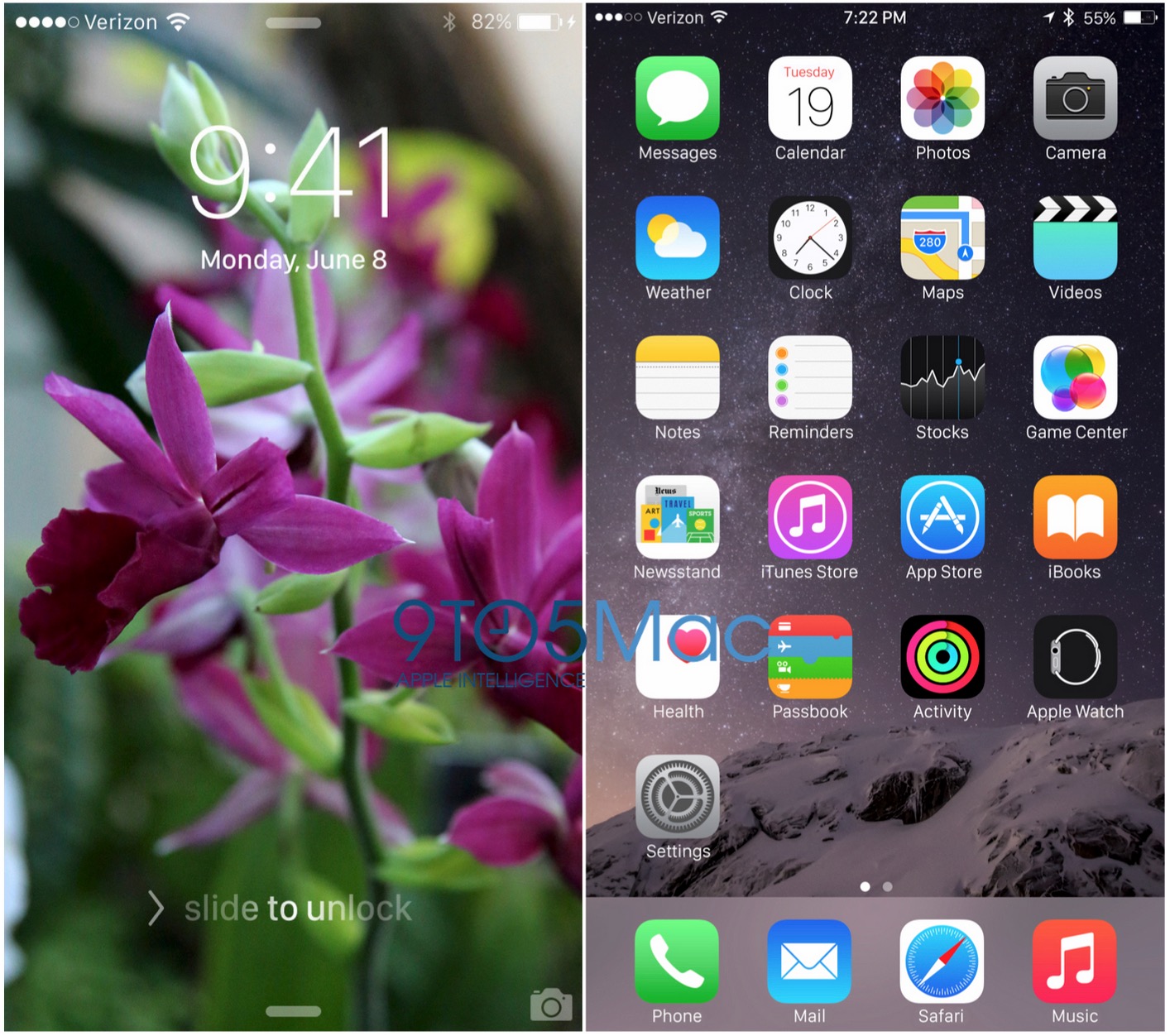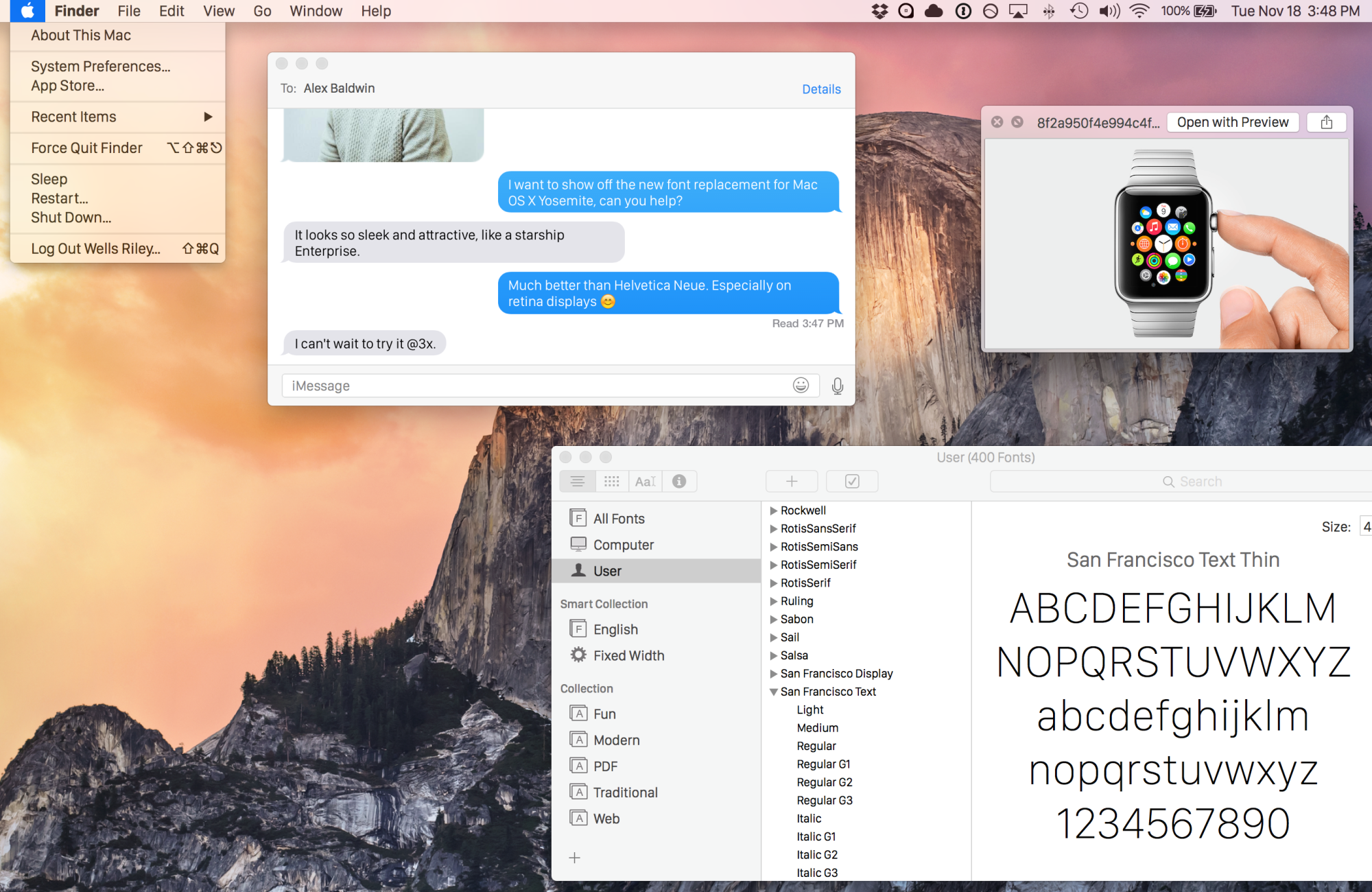
มีรายงานว่า Apple มีแผนที่จะใช้ตัวอักษรใหม่กับ iOS 9 ซึ่งจะมีแทนที่แบบเดิม ณ ตอนนี้ของ iOS 7, 8 ซึ่งใช้ Helvetica Neue อยู่ โดยพบว่าตัวอักษรใหม่นั้นมีชื่อว่า San Francisco ที่ใช้งานใน Apple Watch อยู่ ณ ตอนนี้
หน้าตาของแบบอักษรใหม่ตามข่าวที่แจ้ง (แบบปัจจุบัน iOS 7, 8 อยู่บนสุด)
ตัวฟอนท์ San Francisco นี้เห็นว่าอ่านง่าย, ปรับสเกลง่ายกว่าของเดิมจึงเป็นผลดีต่อนักพัฒนามากขึ้น
นอกจากฟอนท์นี้จะลงใน iOS 9 แล้วก็มีข่าวต่อว่าจะลงที่ OS X 10.11 ด้วยนะ ดังนั้นก็เลยมีคนแฮ็กเอาตัวฟอนท์ที่ว่านี้แทนที่ของเดิมซะเลย ภาพก็เลยออกมาได้ดังนี้ครับ